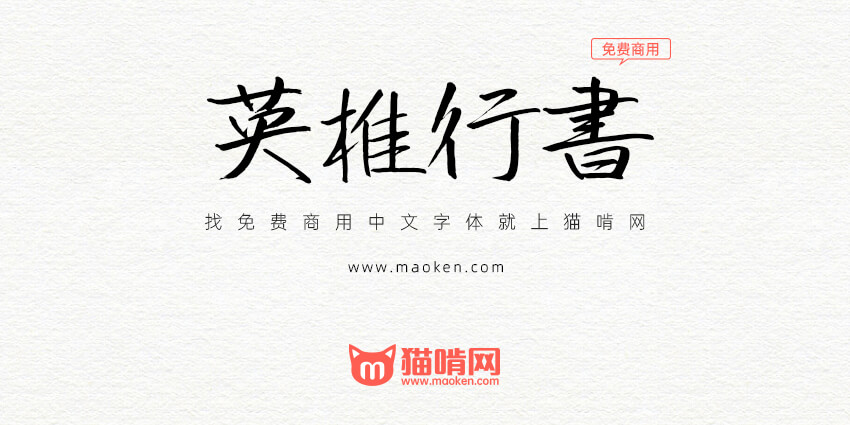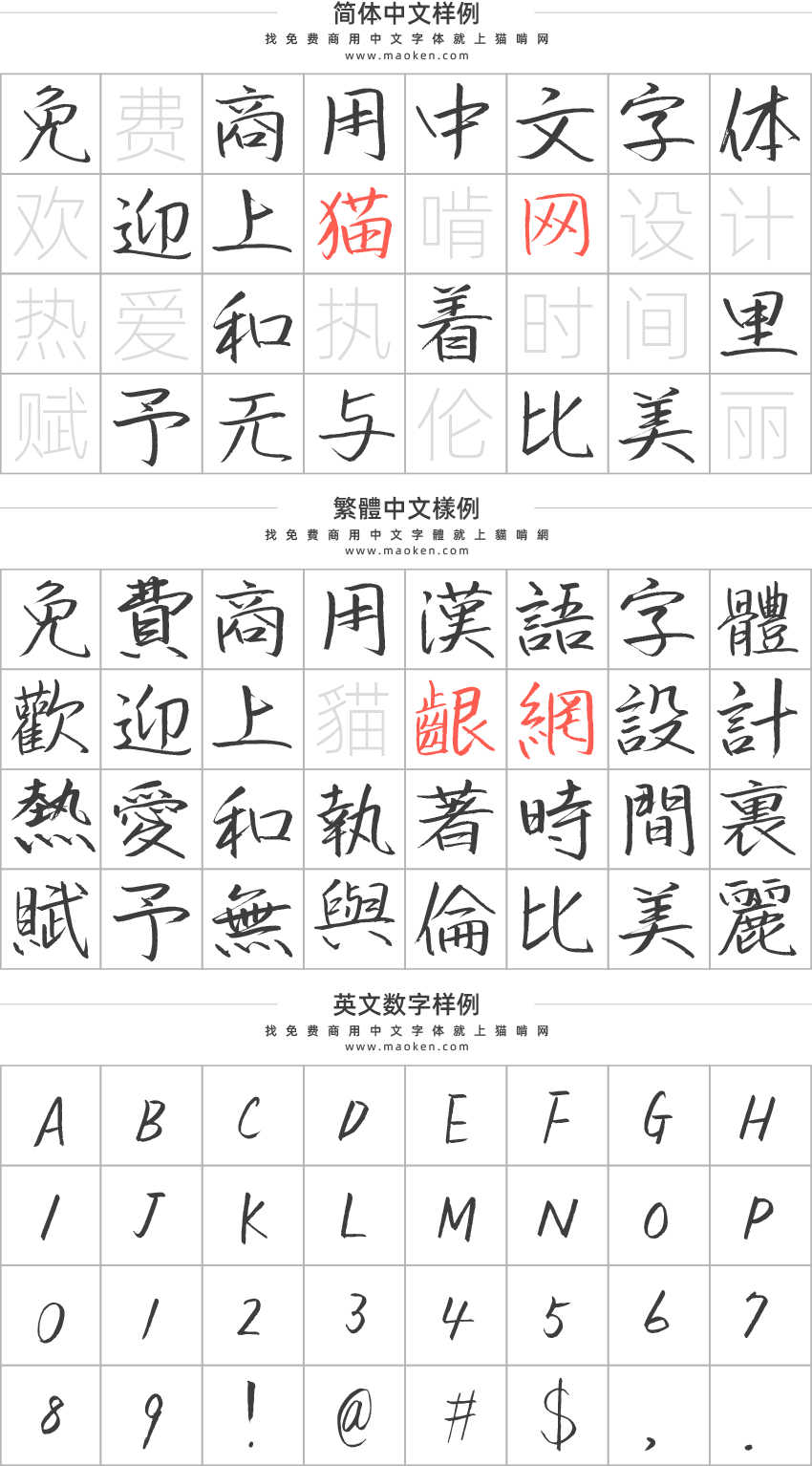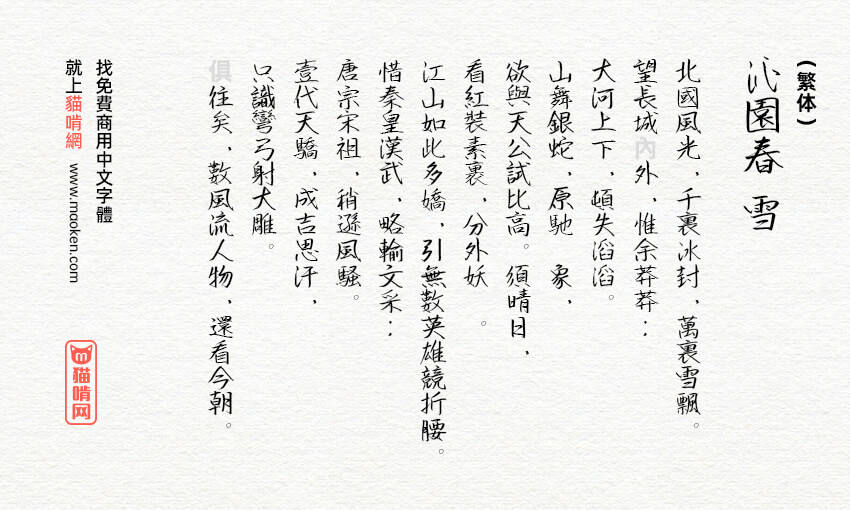
英椎行书:字迹工整漂亮的日系行书字体免费商用
英椎行书是日本acfont自己手写开发的一款字体,这款字体端庄雄伟,书写工整,是一款十分好看的手写字体。英椎行书共收录了6879个文字,因为日文字符一般是以JIS水准为标准,所以繁体字支持得比较完整。简体字数相对较少,不过也确实是一款难得的字体。喜欢的朋友赶紧下载吧!